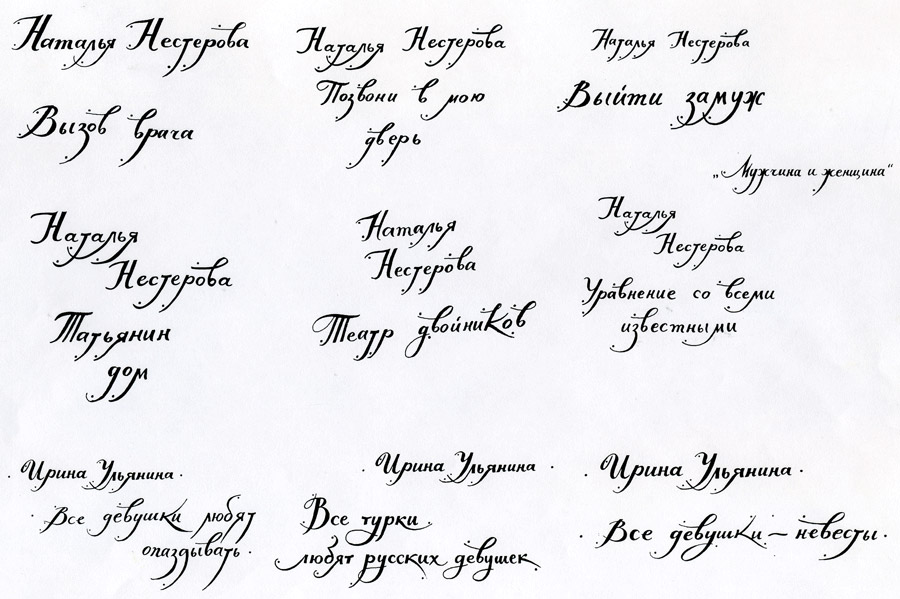
Шрифты “от руки”: учимся рисовать
В эпоху социальных сетей и смартфонов в скором времени в обществе станут появляться люди, которые лишь понаслышке будут знать, что такое письма от руки. Меньше всего в современном мире человек при желании общаться с родными и близкими заботится теперь о написании бумажных писем.
Проще и быстрее отправить короткое текстовое или звуковое сообщение, но что если вам захочется выразить свои чувства при помощи писем от руки?
Как воспользоваться рукописным текстом, какие рукописные шрифты бывают и где их найти, об этом поговорим в сегодняшнем посте. Единственное, что мы можем сказать с полной уверенностью, даже непрофессионал и человек далекий от понимания каллиграфии сможет воспользоваться приведенными ниже примерами, чтобы создать красивое, яркое и незабываемое письмо. Методы отлично подойдут и тем, у кого от природы ужасный почерк. 😉
Начнем с пошагового плана. И для начала выберем несколько интересных шрифтов, которые будем использовать при создании письма.
Всему нужна основа
Прежде всего вам необходимо набросать структуру своих будущих писем. Одна из самых распространенных ошибок – игнорирование начальных шагов, спешка и жгучее желание добиться результата как можно быстрее. Ваше письмо и в целом стиль рукописного ввода будут выглядеть привлекательнее, если сначала создать скелет.
После подготовки основы для будущего рукописного сообщения можно переходить к буквам. Здесь также не стоит торопиться, тщательно прорисованный элемент требует усердия и времени.
Дальше можно оживить буквы и слова элементами выбранного шрифта. Не бойтесь экспериментировать с кривыми и плавными линиями и т.д.
Предлагаем ознакомиться с предложенными ниже видео, чтобы научиться каллиграфии.
Как научиться современной каллиграфии. Пособие для новичков
Как писать каллиграфическим почерком
Сценарий каллиграфии для начинающих – бесплатные рабочие таблицы!
Кисти для письма – 8 основных штрихов для каллиграфии
ТОП-15 рукописных шрифтов
Если вы не хотите изучать каллиграфию самостоятельно, но хотите использовать красивые рукописные шрифты на своем сайте, воспользуйтесь уже готовыми наборами шрифтов. Мы подготовили подборку из 15 лучших рукописных шрифтов от
ТОП-15 рукописных шрифтов 2019
Очень много было написано о дизайне шрифтов, особенно об истории их создания. Мы читали о множестве техник создания шрифтов. Но откуда, собственно, нужно начинать? Если вы – дизайнер или иллюстратор, и эта дисциплина вам в новинку, то с чего же вам начинать?
Мы нашли полезную информацию, которую собрали с множества источников, и решили собрать все воедино.
1. Начните с брифа
Создание шрифта – это долгая и кропотливая работа, поэтому очень важно иметь четкое понимание того, каким должен быть этот шрифт.
Разработка брифа безусловно потребует исследований и раздумий. Как будет использоваться ваш шрифт: он понадобится для специфического проекта или для личного пользования? Есть ли проблема, которую ваш шрифт решил бы? Впишется ли ваш шрифт в массив похожих дизайнов? Что делает его уникальным?
Вариантов много. Шрифты могут быть созданы, к примеру, специально для академических текстов или для плакатов. Только когда вы будете знать, как ваш шрифт может быть использован, тогда вы будете готовы начинать дизайн.
2. Фундаментальный выбор
Существует некоторое количество решений, о которых нужно помнить. Будет ли это рубленный шрифт или с засечками? Будет ли он основываться на рукописном тексте или будет более геометричным? Будет ли шрифт создан для текста и подходить для длинных документов? Или может он будет отображать текст в креативном стиле и будет лучше смотреться в крупном размере?
Подсказка: Предполагается, что дизайн рубленного шрифта дается начинающим сложнее, так как возможности таких шрифтов более специфичны.
3. Подводные камни на ранних этапах
Есть несколько подводных камней:
- Вы можете решить начинать с компьютеризации рукописного шрифта, что может быть полезным практическим упражнением. Но из-за того, что почерк очень индивидуален, ваш шрифт может не иметь большого успеха из-за своей специфичности.
- Не стоит брать за основу существующие шрифты. Переделав немного уже знакомый всем шрифт, вы не создадите шрифт получше и не разовьете свои навыки.
4. Используйте свои руки
Существует много материалов на тему того, как рисовать шрифты с помощью компьютерных программ, но мы настойчиво рекомендуем вам сначала нарисовать его от руки. Попытки сделать это на компьютере существенно усложнят вашу работу.
Попробуйте создать красивые формы первых нескольких букв на бумаге, а уже потом начинайте компьютерную работу. Следующие буквы потом могут быть сконструированы на основе существующих форм, в соответствии с ключевыми особенностями.
15. Mazak
Этот крупный шрифт выделяет штрихи маркера, придавая ему крутой грубый вид. Он написан заглавными буквами, что делает его хорошим вариантом для больших дизайнов, таких как плакаты.
16. Луна
Этот свежий чистый рукописный шрифт, созданный Амандой Лисон, имеет большой контраст между буквами и линиями, что делает его очень разборчивым.